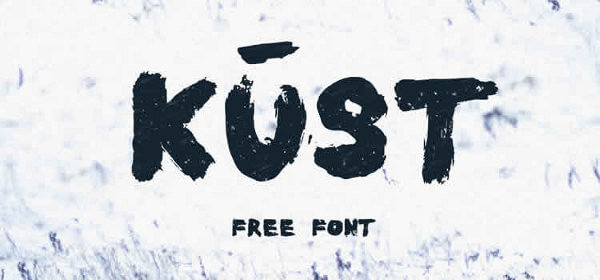
「毛筆の美」を再発見!無料で使えるユニークなブラッシュ・スタイル・フォント15選
いびつな形で不規則、にもかかわらず美しさを感じさせるような不完全さ。
どの文字もひとつひとつがユニークで、丁寧にハンドメイドされている。
ヴィンテージ・スタイルであるにもかかわらず、モダンさを併せ持つ。
毛筆スタイルのタイポグラフィは長い間忘れられていましたが、いまその美しさが再び注目されています。
本記事では、15のフリー・ブラッシュ・フォントを紹介します。
Besom Brush Font Designed by Krisijanis Mezulis & Gatis Vilaks
Dallegrave Free Brush Typeface Designed by Gianlucca Segato
Hensa Free Brush Script Font Designed by Vlad Cristea
Duwhoers Brush Font Designed by Swistblnk
Kust Free Brush Font Designed by Krisijanis Mezulis
Debby Brush Font Designed by Artimasa Studio
Reckless Brush Font Designed by Nadi Spasibenko
Dreamers Brush Free Font Designed by Hermansy Man
Beacon Free Font Designed by Befonts
BlowBrush Font Designed by Petar Acanski
Selima Free Font Designed by Jroh Creative
Sophia Hand-Lettered Brush Script Designed by Mats-Peter Forss & Emily Spadoni
Brux Bold Brush Font
Mazak Brush Font Designed by Ewelina Gaska
Rosco Free Brush Font Designed by Logoholique